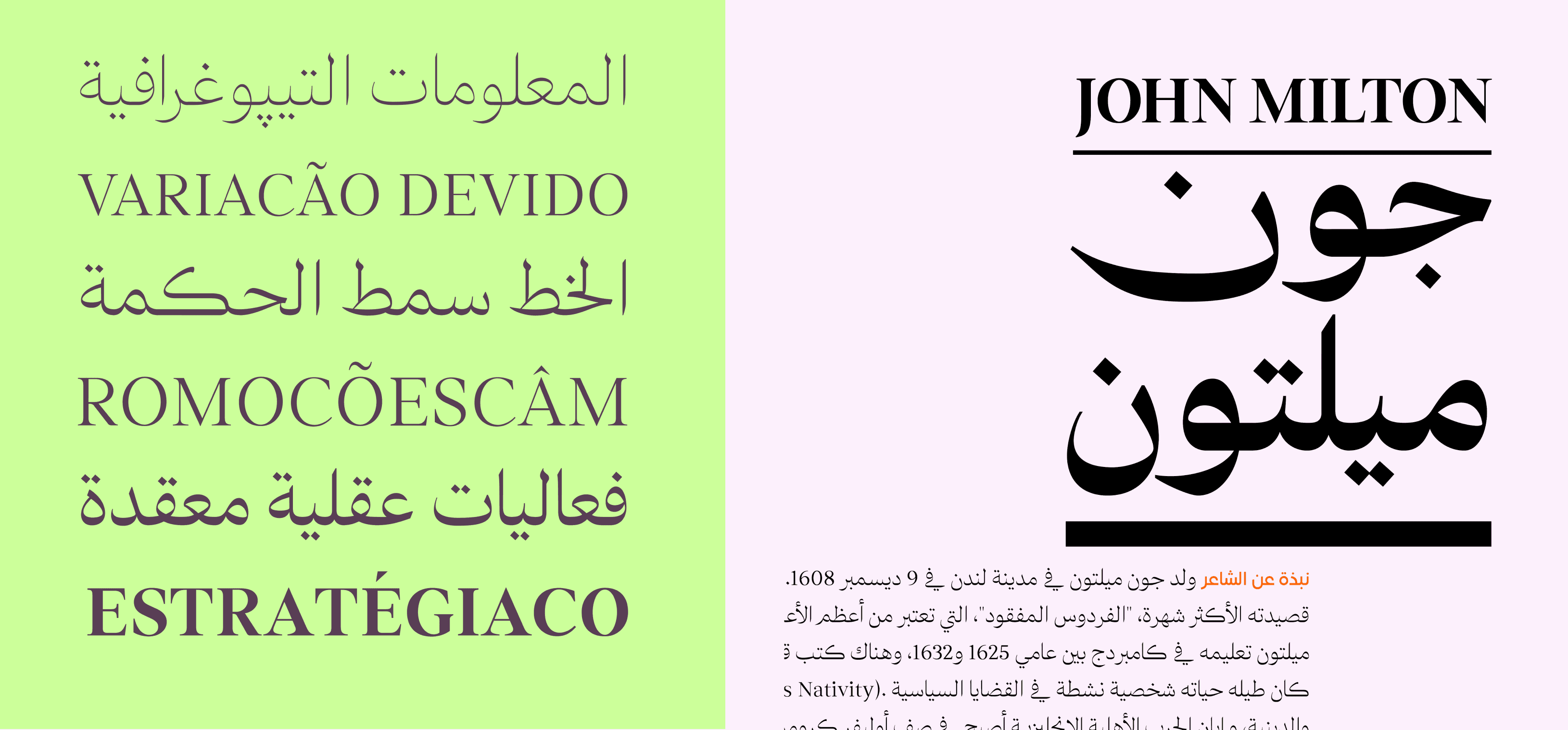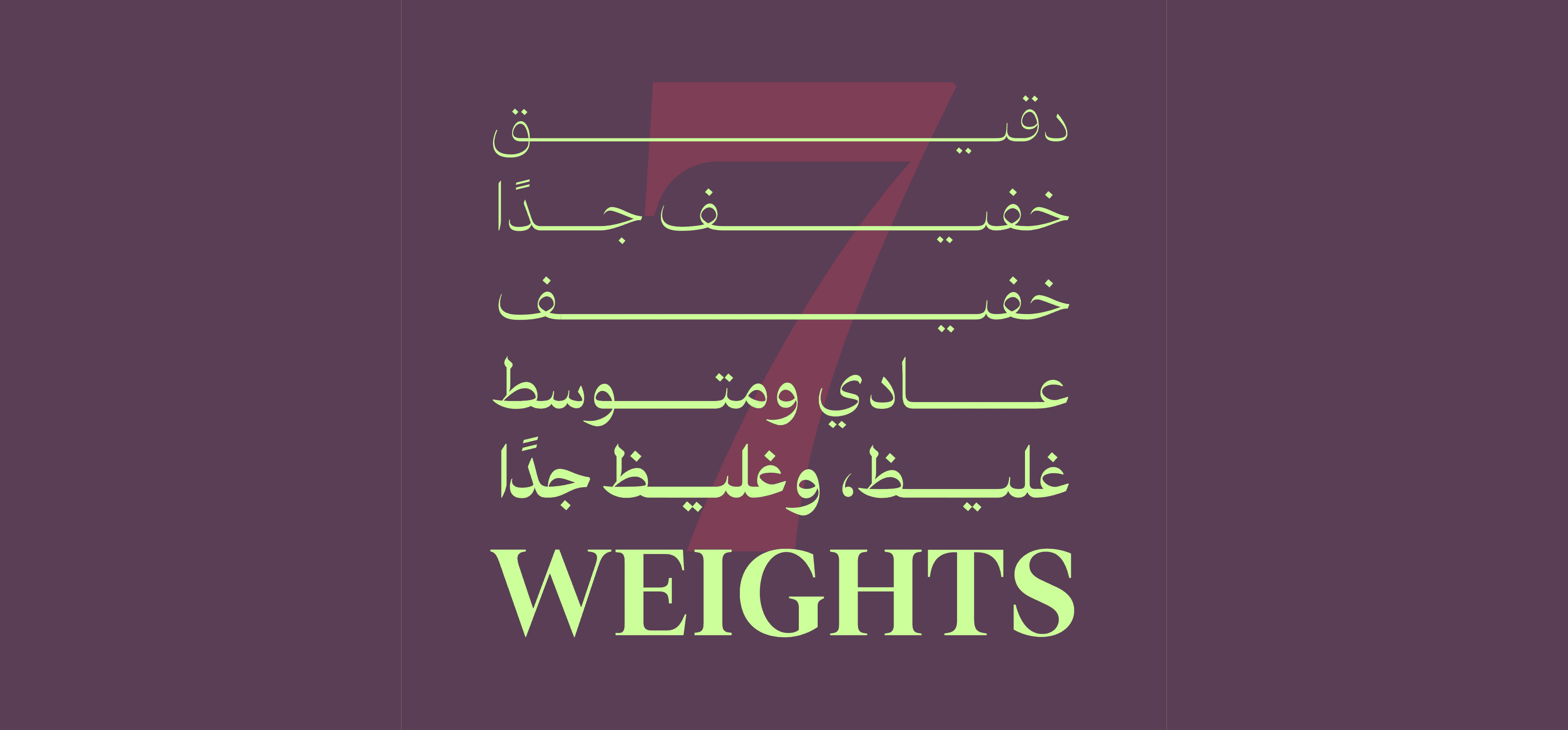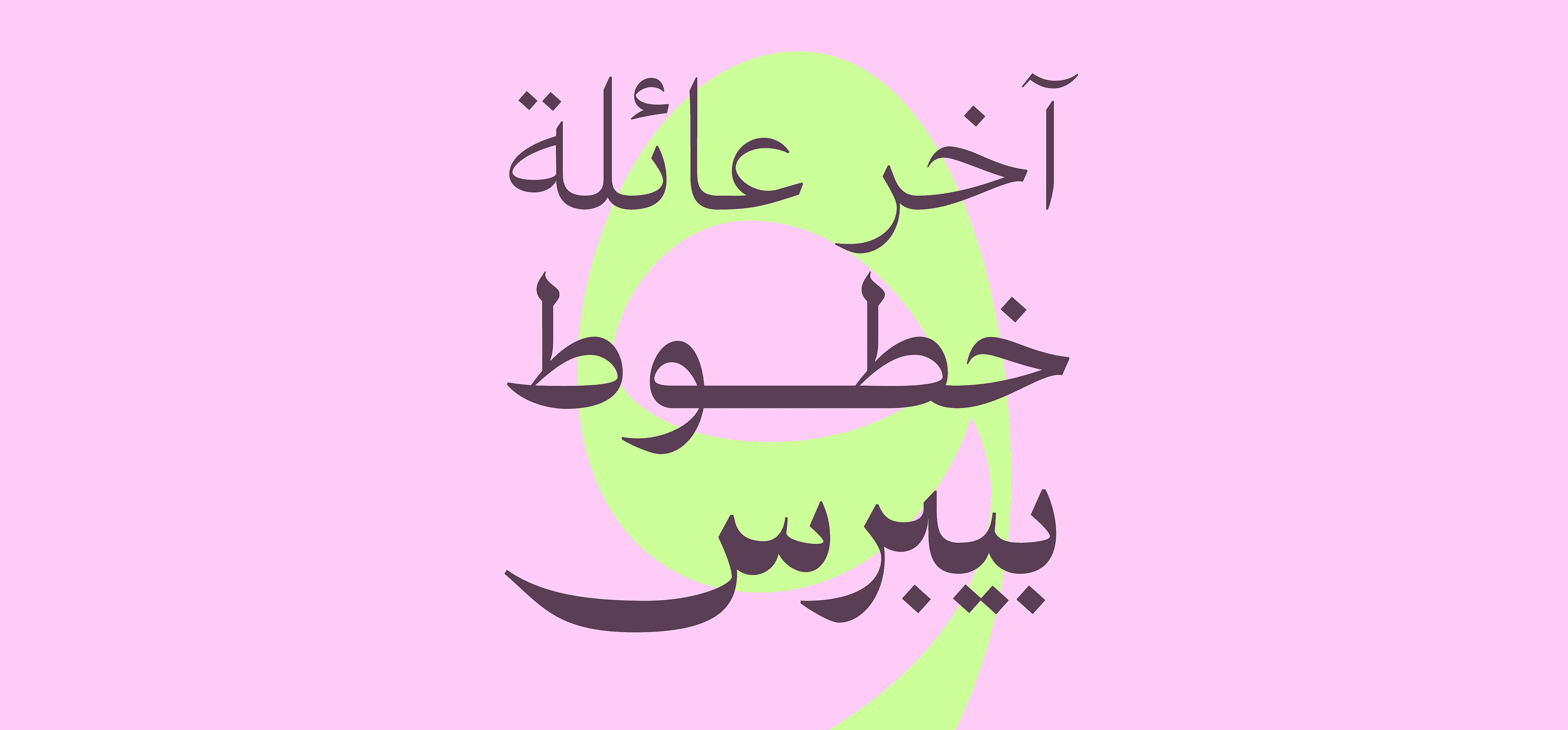
خط بيبرس ديسبلاي – Baybars Display
يُعد هذا الخط جزءًا أساسيًا من نظام خطوط بيبرس المتكامل، ويتميز بتصميمه النَّسخي الأنيق والديناميكي.
يمزج بين العناصر الفريدة والتكوينات الكلاسيكية، مما يمنحه توازنًا بصريًا راقيًا يناسب العناوين، التحرير الصحفي، والمجلات.
بيبرس ديسبلاي خيار مثالي للمشاريع التي تتطلب حضورًا typographic قويًا يدمج الحداثة بالأصالة.